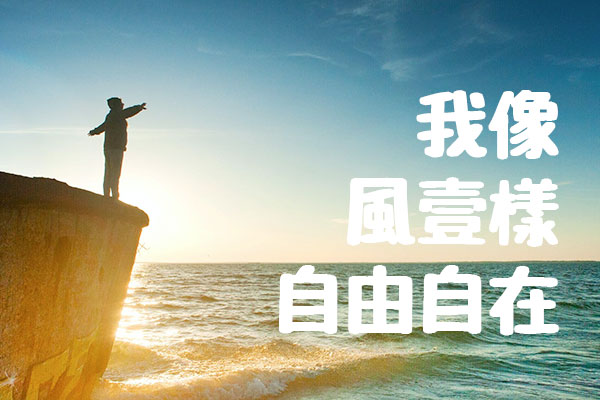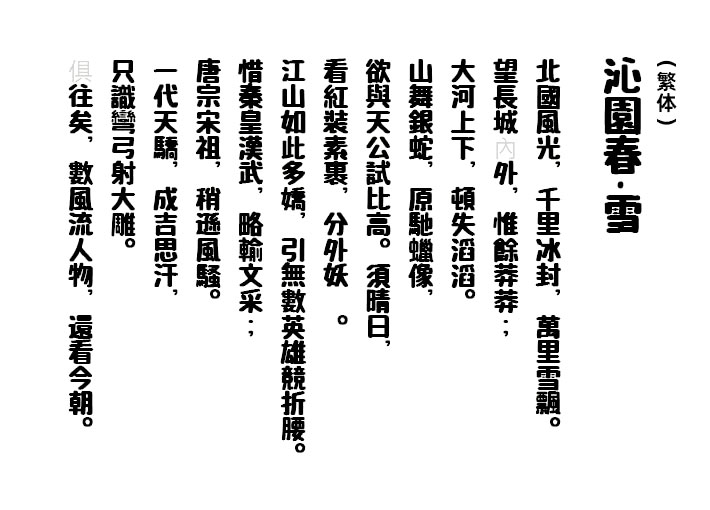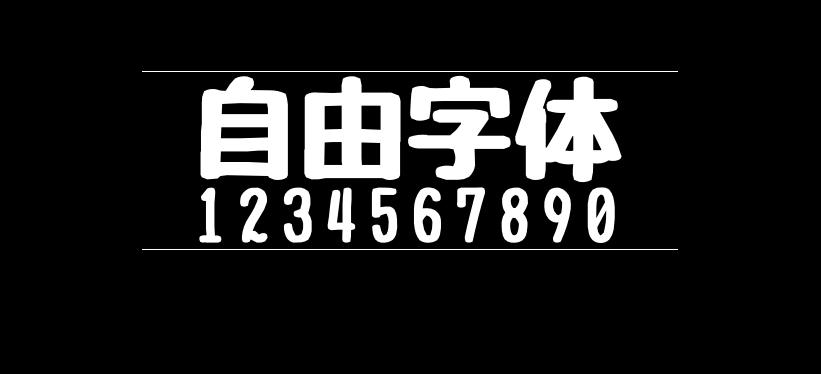
自由字体
自由字体(じゆうちょうフォント、Jiyucho)是日本的よく飛ばない鳥推出的一款免费商用日文字体,是一款圆形文字风格的手写字体,有点像用粗记号笔写的那样,以温暖的黑体为目标而制作的。
自由字体因为笔画较粗,特别适合用于标题的设计,它既有黑体的特征,又比黑体多了一分手写的痕迹。
自由字体包含简体中文字体4402个,其中常用字2470个,繁体字相对更多一些。这款字体自由君非常喜欢,因为它够粗够黑,而且跟自由字体网站同名,如果能有更多的简体字就更好啦!